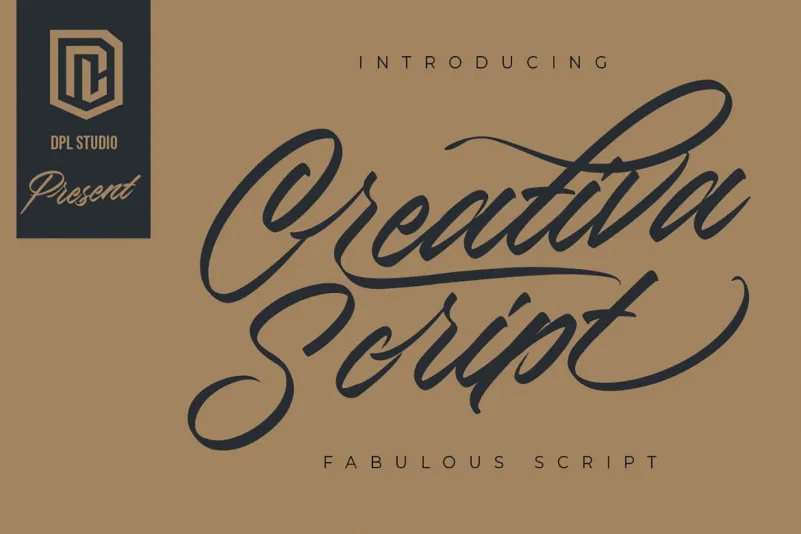
Creativa Font – Fonte Grátis
Creativa Font
Esta é uma fonte em estilo script criada pela DPL Studio com um design contemporâneo. Ela transmite uma sensação encantadora, autêntica e relaxante, perfeita para adicionar um toque natural às suas criações. Além disso, essa fonte traz letras únicas e autênticas que certamente vão conquistar o seu coração. A Creativa Font é ideal para designers buscando uma mistura de modernidade com uma atmosfera quase mágica e descontraída, tornando-a perfeita para trabalhos diversos como logos, publicações ou até mesmo ilustrações. Seja você um designer inovador ou aquele que gosta de um toque especial em seus projetos, a Creativa Font pode ser uma ótima escolha para adicionar personalidade e frescor aos seus designes.